黑体
黑体字又称方体或哥特体,没有衬线装饰,字形端正,笔画横平竖直,笔迹全部一样粗细。汉字的黑体是在现代印刷术传入东方后依据西文无衬线体中的黑体所创造的。由于汉字笔划多,小字黑体清晰度较差,所以一开始主要用于文章标题。但随着制字技术的改进,已有许多适用于正文的黑体字型。在中文中,没有衬线的字体通常称为黑体,这时这个词的范畴和无衬线字体(Sans-serif)是类似的。所以在中文字体中常用“黑体”,在西文中常用“无衬线体”的称呼。而宋体就可以被称作衬线字体。
黑体与白体相反,没有衬线装饰,笔划粗壮有力,撇捺等笔画不尖,使人易于阅读。黑体是在现代印刷术传入东方后依据西文无衬线体所创造的。所以黑体这个词的范畴和无衬线字体是类似的。而宋体就可以被称作衬线字体。
“黑体”在日文中直译即哥特体。但在欧洲国家中,哥特体指的是Blackletter(日文也根据「Blackletter」的音,称作「ブラックレター」)。因此上述词汇不能直译。
粗体在不正式的的场合里常常也被叫做“黑体”,造成了中文指称的混乱。另外需要注意的是,Windows附带的黑体是由北京中易中标电子信息技术有限公司制作的一个字体。“黑体”是一类字体的总称,有很多字体都属于这个范畴,而中易黑体只是众多黑体中的一种,不应该和字体的“黑体”混淆。 在微软Windows Vista发布之前,中文操作系统的默认字体是宋体或者细明体,它们都属于衬线字体,无论是从审美角度还是从眼睛的承受程度都不及作为无衬线字体的微软雅黑体或者微软正黑体,因为笔划上过多的点缀(笔划末端的小三角)很容易造成视觉疲劳(尤其是显示在屏幕上),所以很多新发布的操作系统为了减少使用时的视觉疲劳而采用无衬线字体作为默认字体。
带衬线的黑体
严格意义上来讲,在汉字字体的一些黑体中也是有衬线的,例如图1第二个字体,在每个笔画的端口都有一个喇叭口形状的装饰,这种装饰源于早些时候的铅字印刷的铅字,由于当时技术的限制,笔画的端口会收缩,为了解决这个问题,当时设计铅字的工作人员就把黑体设计成喇叭口的。以致后来的计算机时代,在设计首批黑体的时候,参照了有喇叭口装饰的黑体,所以早期的Windows XP,Mac OS中的“中易黑体”和“华文细黑”都是带有喇叭口的。而另外一种有装饰衬线的黑体,是参照人工用板刷写的黑体,因此在这些黑体当中,竖笔、提点、撇等笔画中会在起笔处带有小圆点装饰,例如“方正韵动黑”正是这样的字体,如图1最后一个字体。这些带有衬线的黑体相对于宋体来说,这些衬线只是线条上的细微的变化,几乎不算什么。所以按照分类,还是把这些有衬线的黑体分类放到无衬线字体当中。
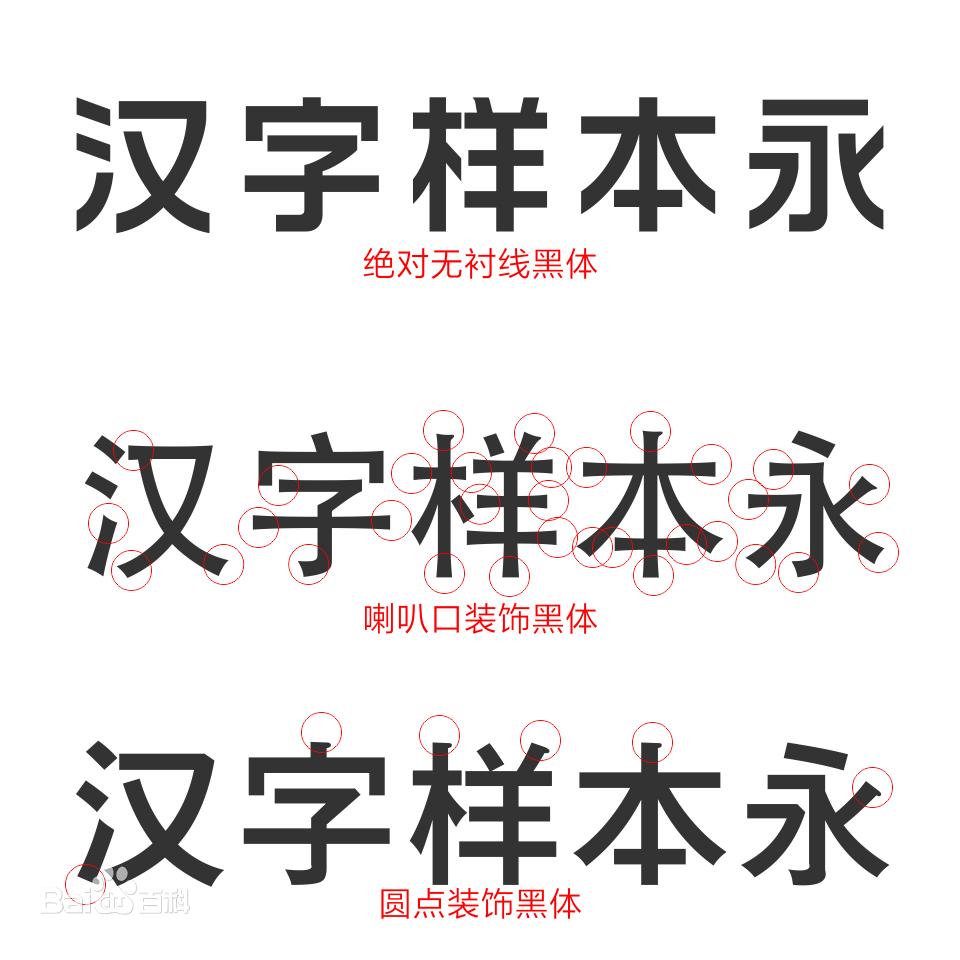
常见的黑体
思源黑体、黑体、大黑、方正超粗黑、方正兰亭黑、方正等线黑、方正俊黑、汉仪中黑、汉仪超粗黑、汉仪中等线、汉仪文黑等黑体,其中思源黑体可以免费商用。